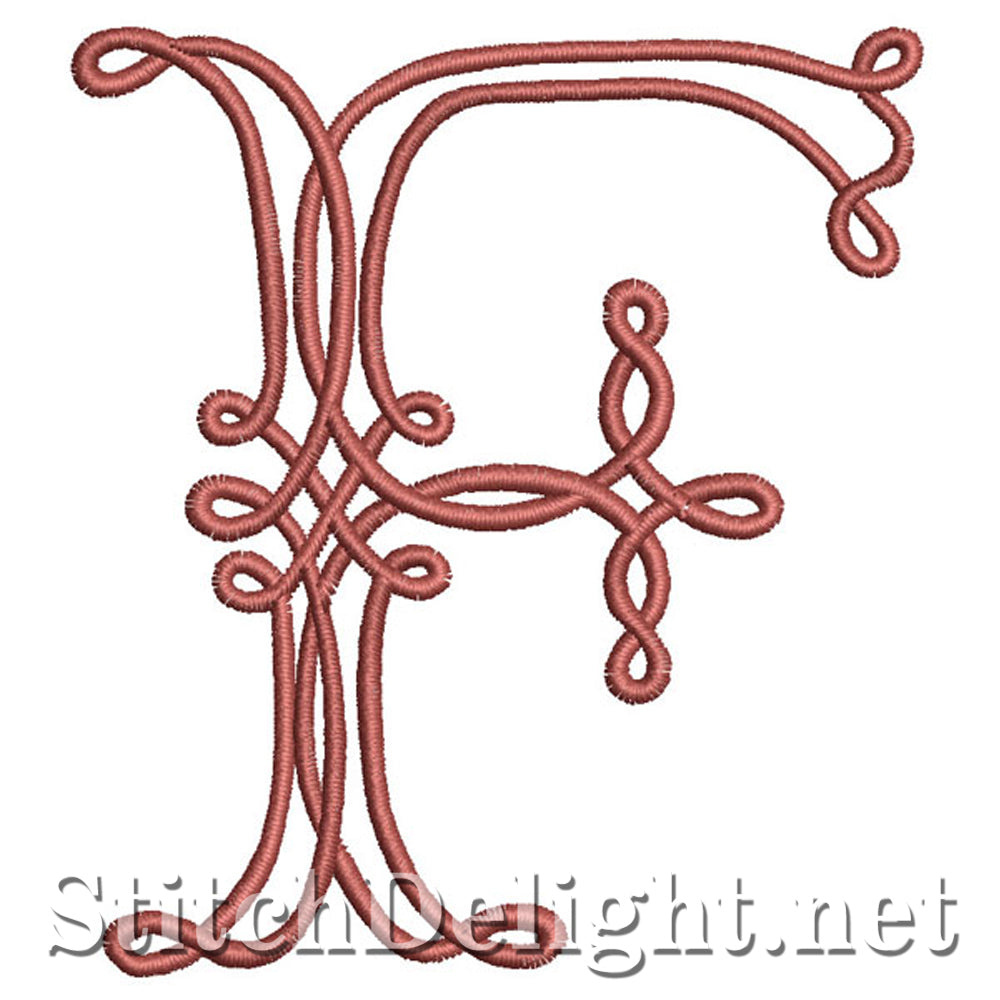
SDS1199 Police celtique F
Police celtique détaillée principalement pour le cerceau 4x4, M, W et Q sont pour le cerceau 4x7, alors assurez-vous de vérifier les tailles pour vous assurer qu'il s'adaptera à votre zone de point - La hauteur des lettres est de 85 mm / 3,34 pouces